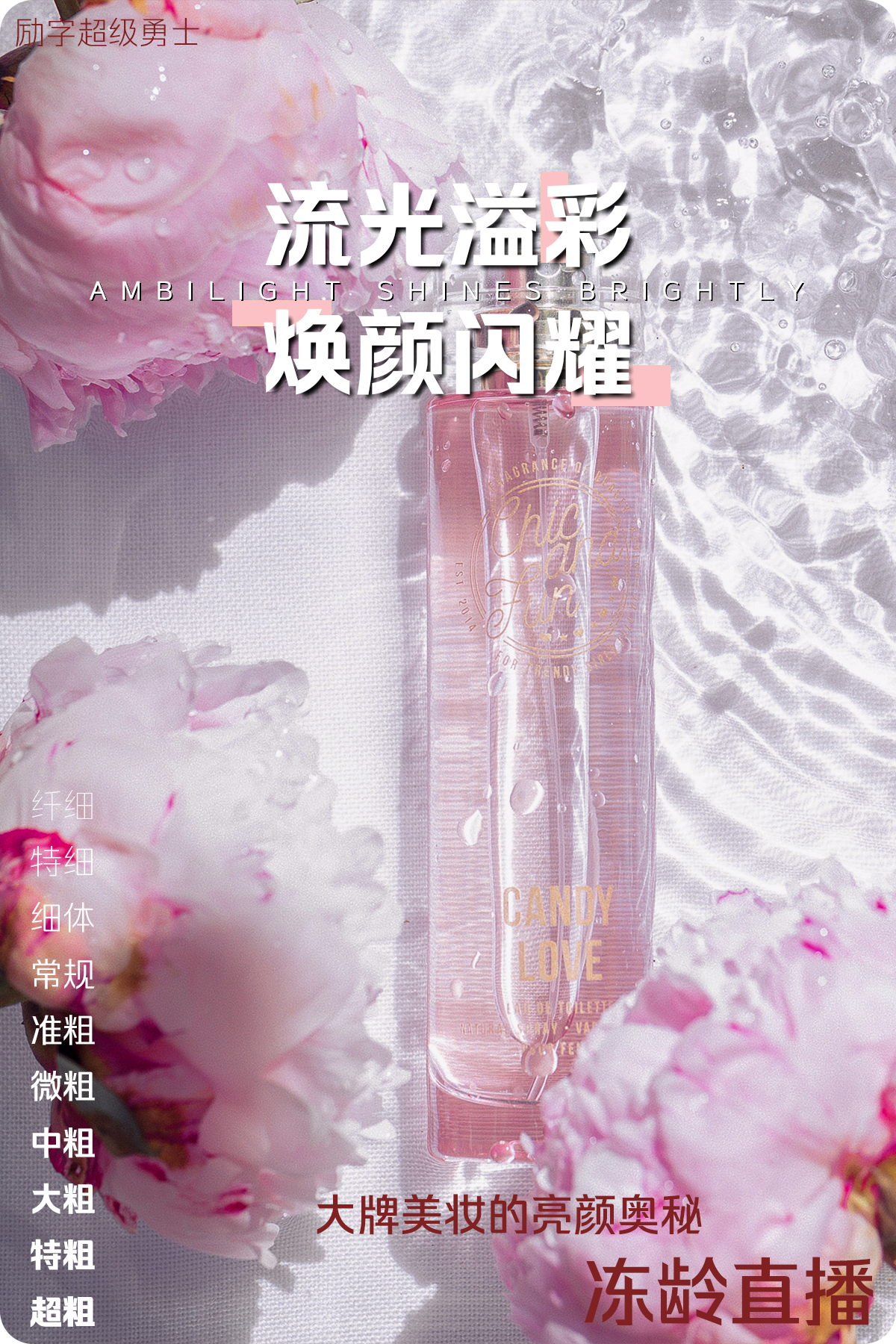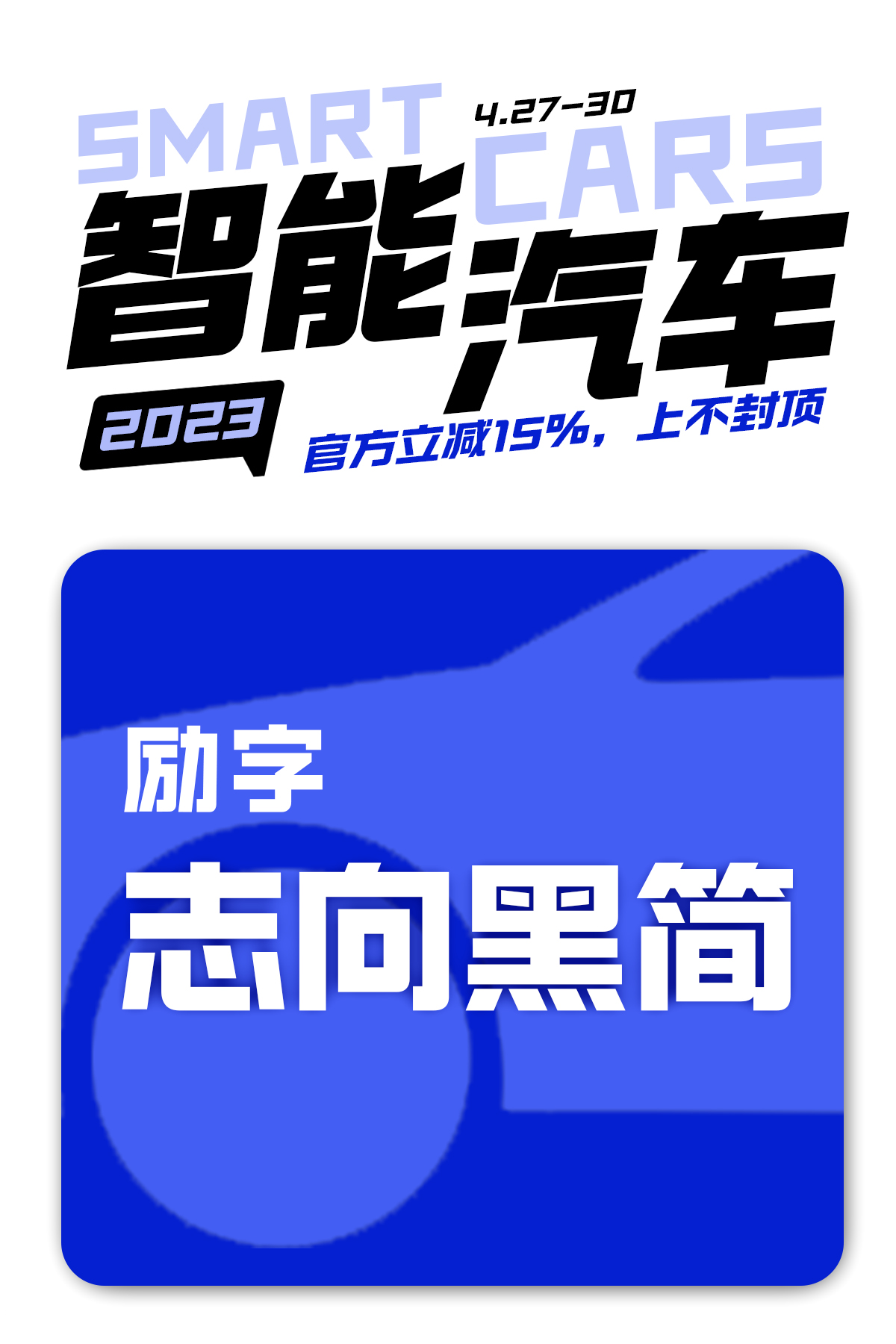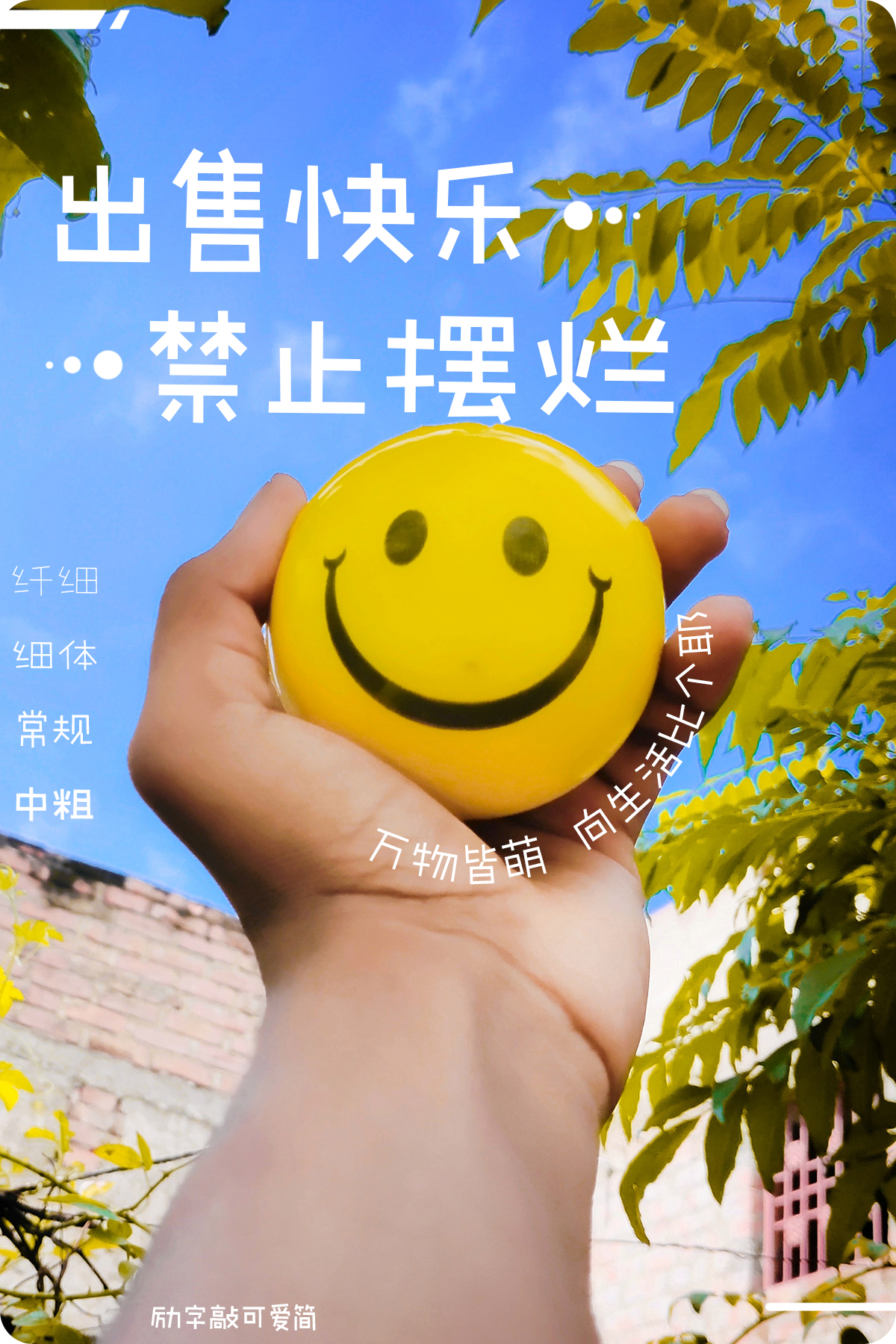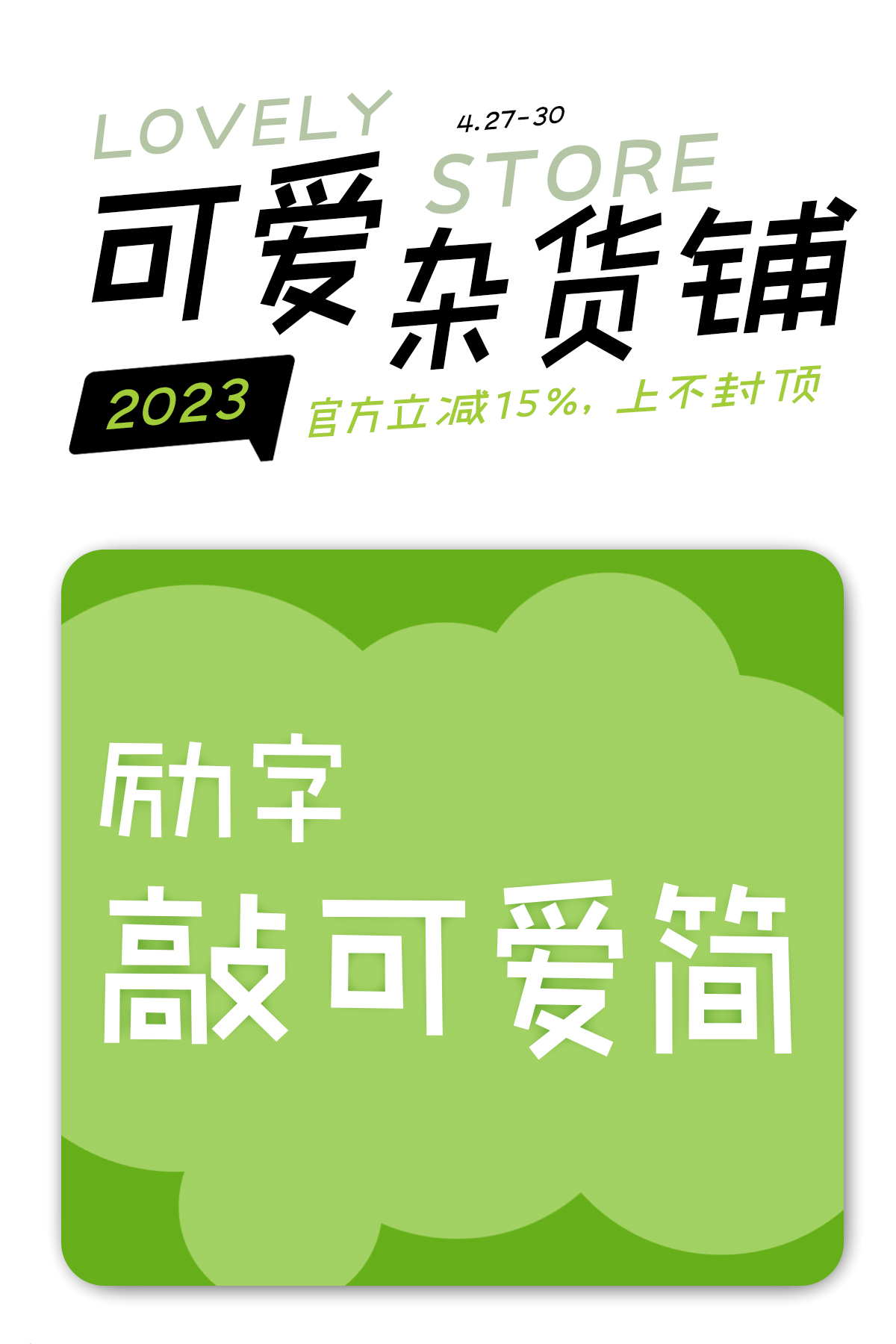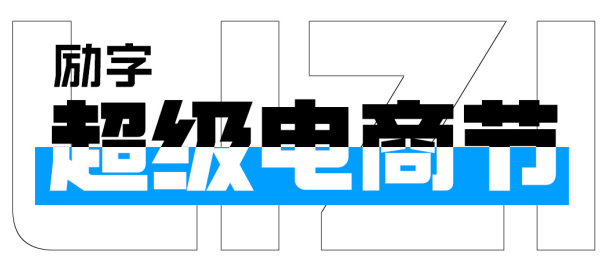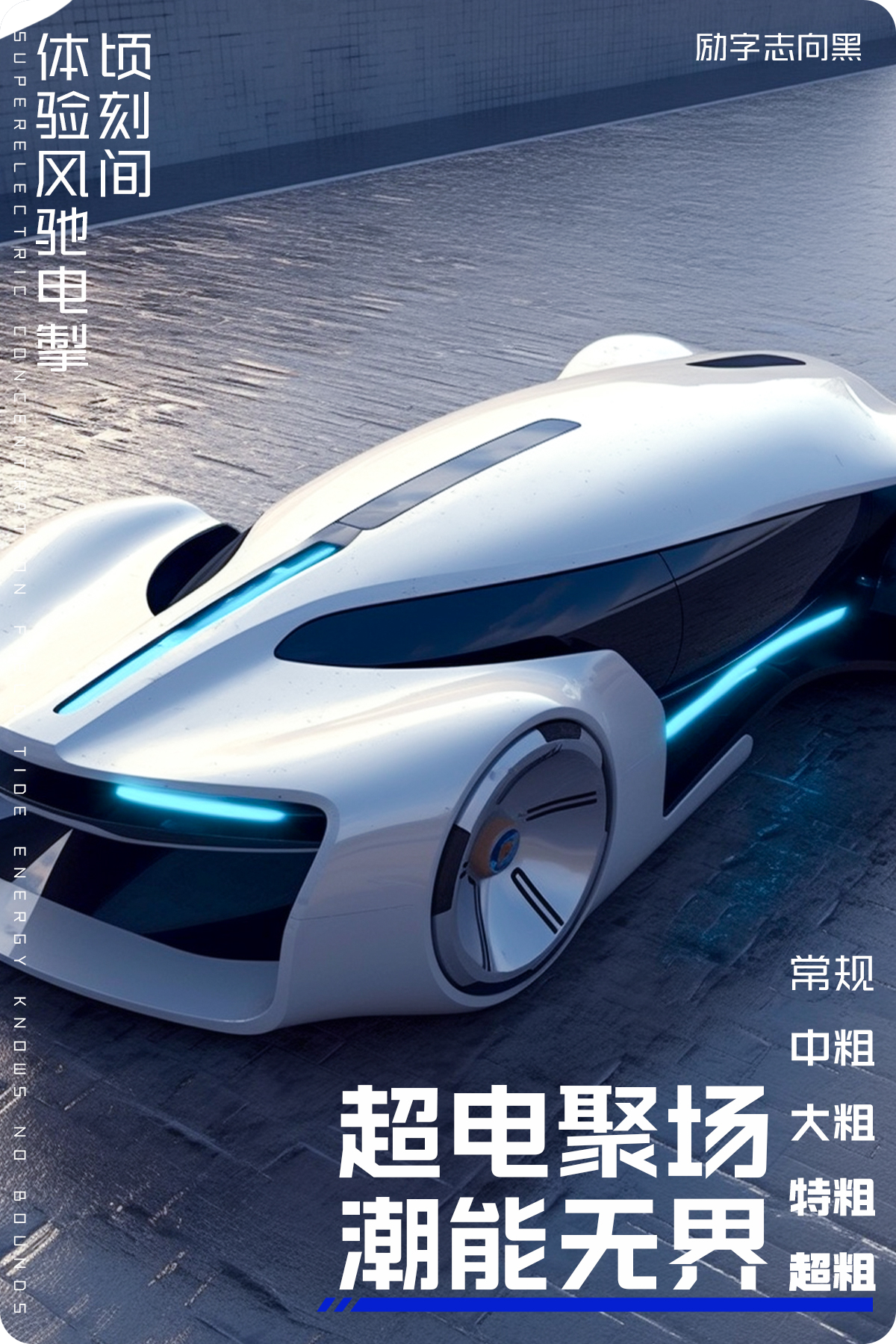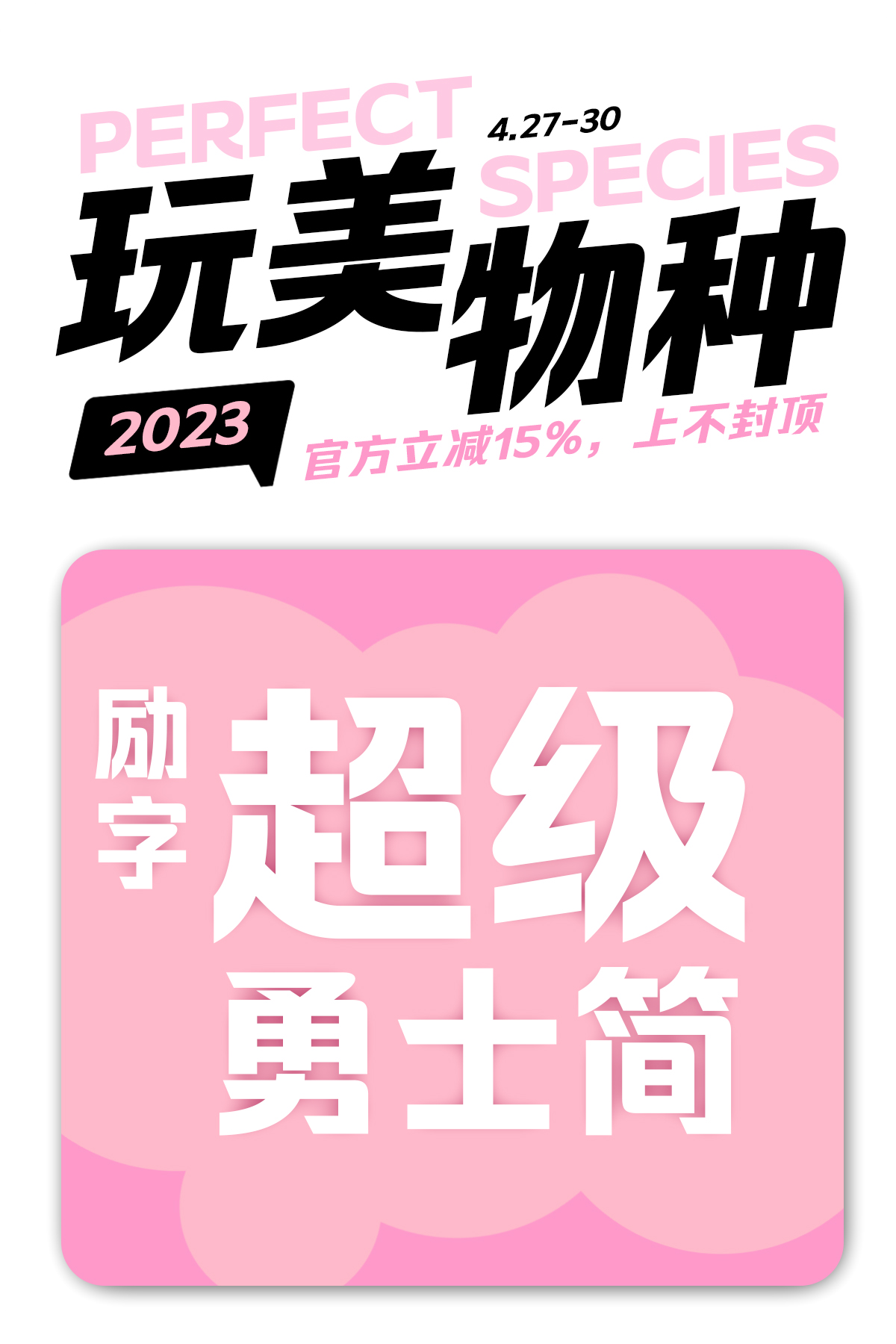
励字超级电商节,多种字体场景,妥妥拿捏!
超级电商节都是各大品牌营销活动的必争之地,各大商家明争暗斗、血雨腥风,各种优惠促销、现金补贴轮番上阵。如何抢占视觉高地,在花样百出的竞争,一举吸引目标客户?励字造梦字库给你的答案。
以粗细均匀的直线笔画诠释智能汽车的极简数控,
笔画起止端平切、直切的设计,
更契合智能屏显系统识别读取,
折笔处采用外圆角设计,彰显流畅丝滑的人车合一体验。
起笔处倾斜和平直设计灵活处理,灵动妆效跃然纸上,
折角笔画由外圆角与方角有序组合,正如美妆叠加时的完美搭配,
撇捺弧度饱满,流畅度、亲肤感满分。
一款粗细均匀、简约有趣、具备手写感的直线字体。
布白空间通透,字形大小不一。整体笔画切口自然,具备手写特点,笔画设计简洁而不呆板。“弯钩笔画、钩笔画”做简化进行去钩处理。